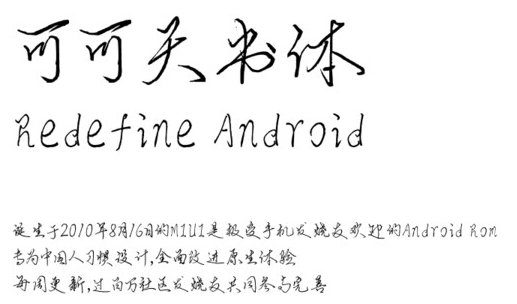
天書體ttf字體是一款字跡連貫的硬筆行書字體,微顯草書字體風(fēng)格二色,給人流暢清爽的藝術(shù)效果,極具古風(fēng)字體的飄逸之美,來綠色資源網(wǎng)搶先使用吧!
可可天書體是在段寧硬筆行書字體的基礎(chǔ)上優(yōu)化而來,該字體瀟灑飄逸,筆畫優(yōu)美,顯示效果好。
可可天書出自可可字體的設(shè)計師段寧之手,結(jié)合了硬筆書法字體和行書字體的風(fēng)格,給文字更加傳神的復(fù)古體驗,造型凌厲張揚,細(xì)節(jié)處卻細(xì)膩樸實,為你的平面設(shè)計增添獨特魅力!